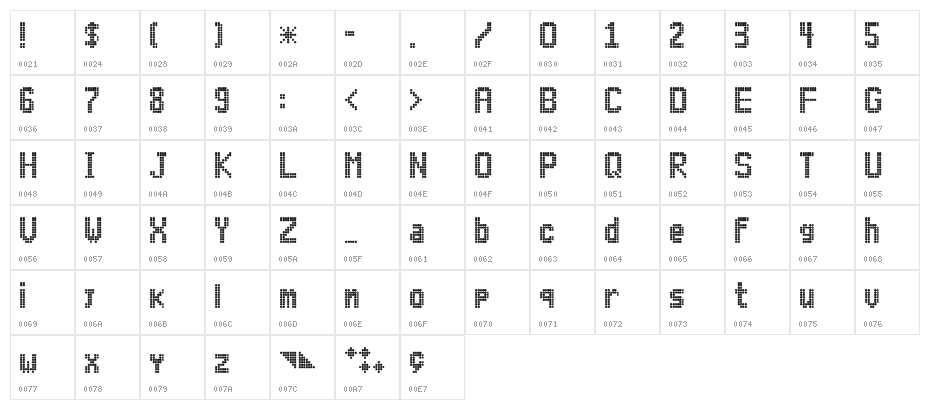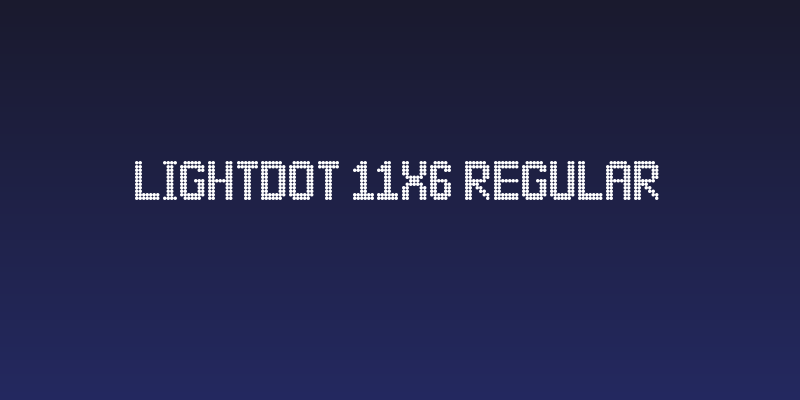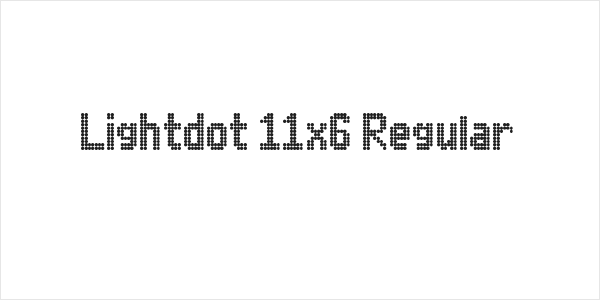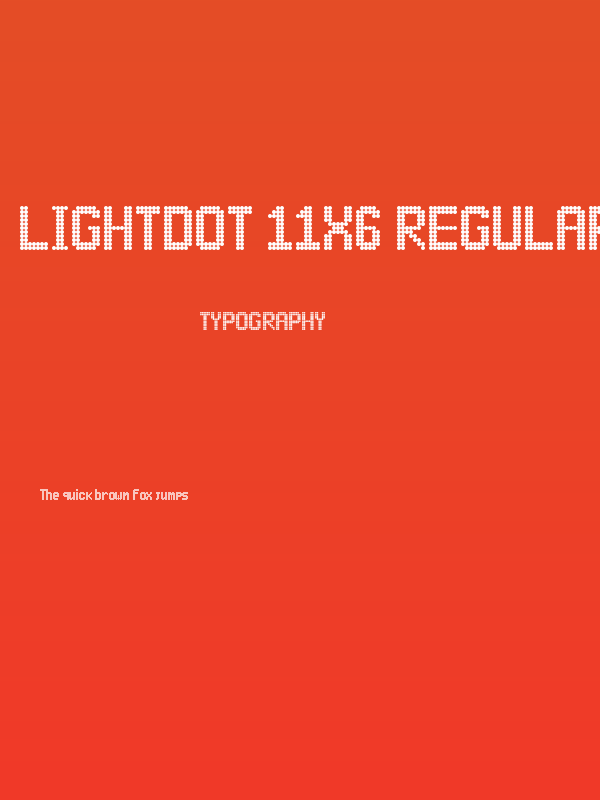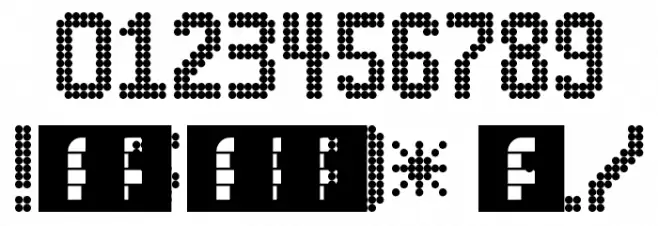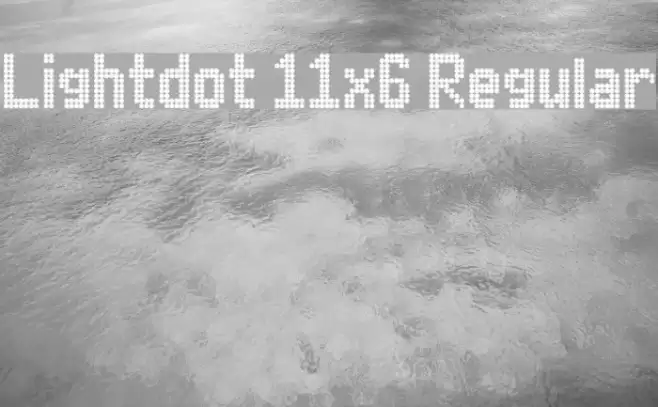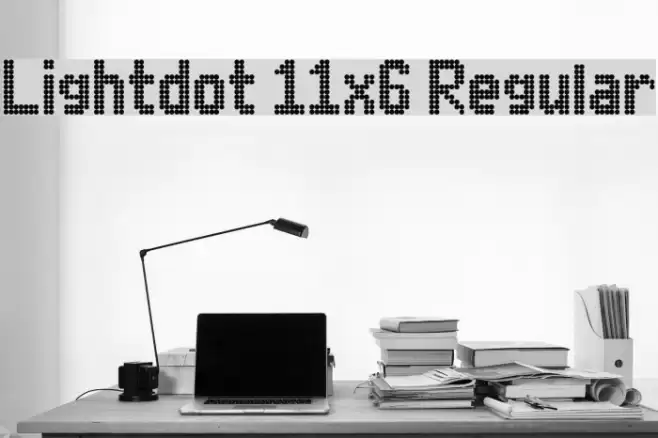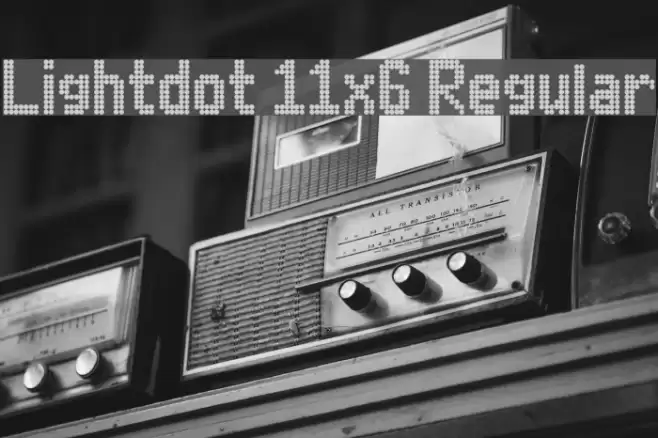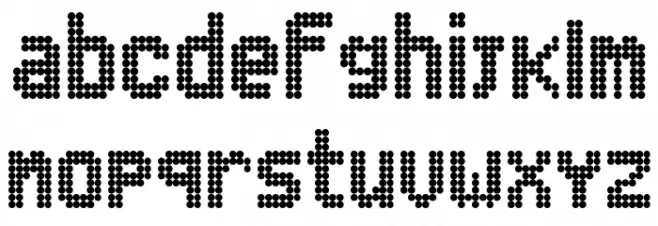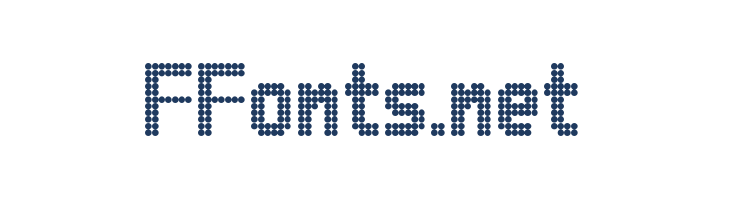
Lightdot 11x6 Regular Font
| Caz de utilizare | Headlines, Logos, Digital displays |
| Proiecte propuse | Ideal for digital displays, tech-themed designs, retro-style projects, and any creative work requiring a futuristic or electronic aesthetic. |